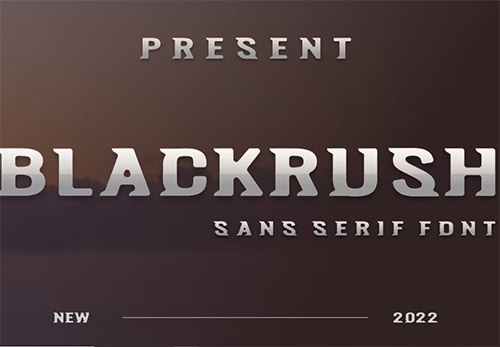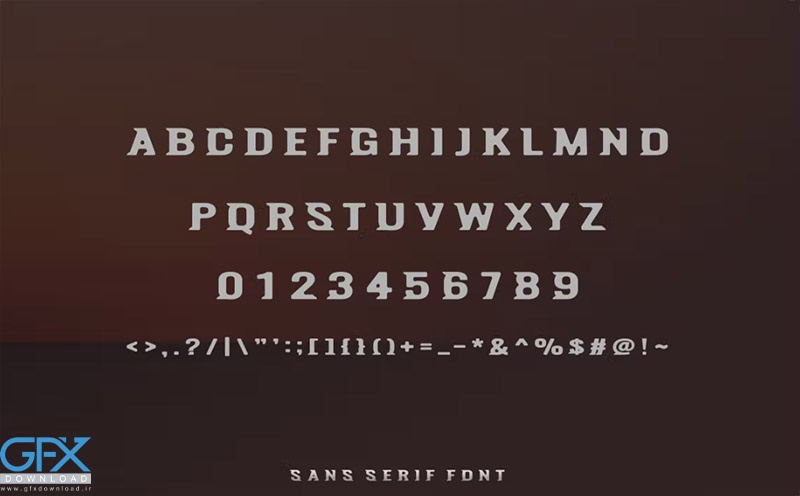
فونت رایگان انگلیسی بولد Blackrush
فونت انگلیسی بولد Blackrush
یک فونت مدرن رایگان بولد و معتبر است. این فونت برای هر پروژه برندسازی مانند لوگو، چاپ تی شرت، esport و بسیاری موارد دیگر مناسب است. فونت رایگان بولد Blackrush در طیف گسترده ای از زمینه ها کاربرد دارد.
این یک فونت انگلیسی پر انرژی و جذاب است و در سبک های مختلف طراحی مانند مسافرت ، آرم ، پوسترهای مراسم و بسیاری از پروژه های طراحی دیگر نیز قابل خواندن و استفاده است.